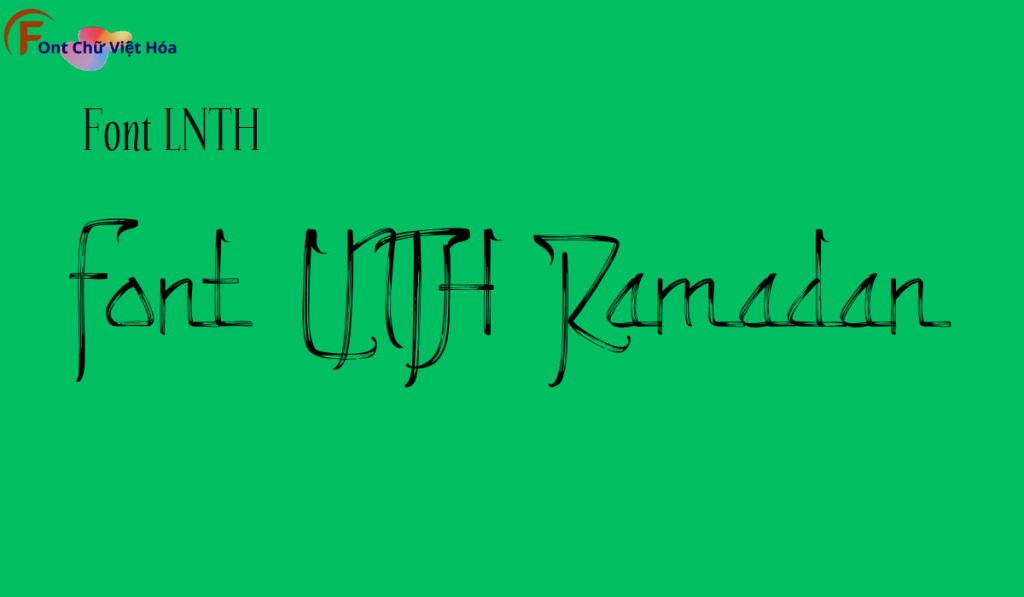
Font LNTH Ramadan Việt Hóa
Font LNTH Ramadan Việt Hóa là một font chữ thư pháp, thuộc bộ LNTH, với thiết kế mang đậm nét văn hóa và tinh thần của tháng lễ Ramadan. Phong cách của font này phù hợp với các dự án thiết kế liên quan đến tôn giáo, lễ hội, hoặc sự kiện văn hóa. Font LNTH Ramadan Việt Hóa mang đến sự trang trọng và dễ nhận diện, ứng dụng trong các lĩnh vực sáng tạo. Đặc điểm hình dạng của font bao gồm các đường nét mềm mại và thanh thoát, giúp tăng tính thẩm mỹ và sự chú ý. Việc Việt hóa font giúp người dùng dễ dàng sử dụng trong các thiết kế tiếng Việt, mang lại sự tiện lợi và linh hoạt.